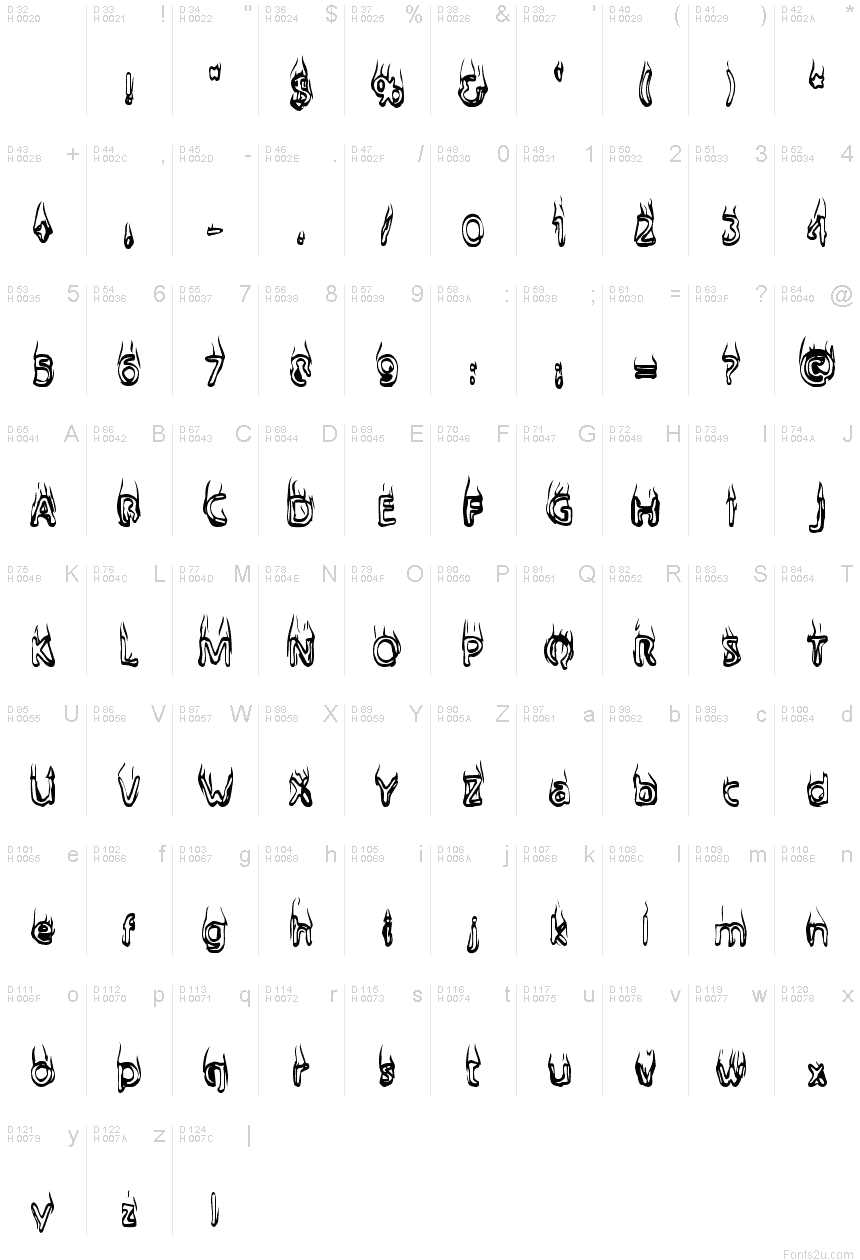
Font BaileysCar od Raye Larabieho je bezplatné dekorativní písmo typu display. Každé písmeno stoupá jako plameny černého inkoustu, s ostrými jazyky a pokřivenými křivkami. Vzhled připomíná směs hot-rod samolepek a strašidelného lesa, což vašim nadpisům dodává divokou, znepokojivou energii.
Při použití fontu BaileysCar působí titulky na hororových plakátech, halloweenských letácích, cedulích strašidelných domů, logách metalových kapel, herních názvech a drsném merchu okamžitě zlovolně. Toto bezplatné písmo nejlépe funguje ve velkém, kde mohou jeho točité tahy dýchat. Zkombinujte ho s prostým, zúženým bezpatkovým písmem v doprovodném textu, aby drama zůstalo soustředěno na hlavní nápis.